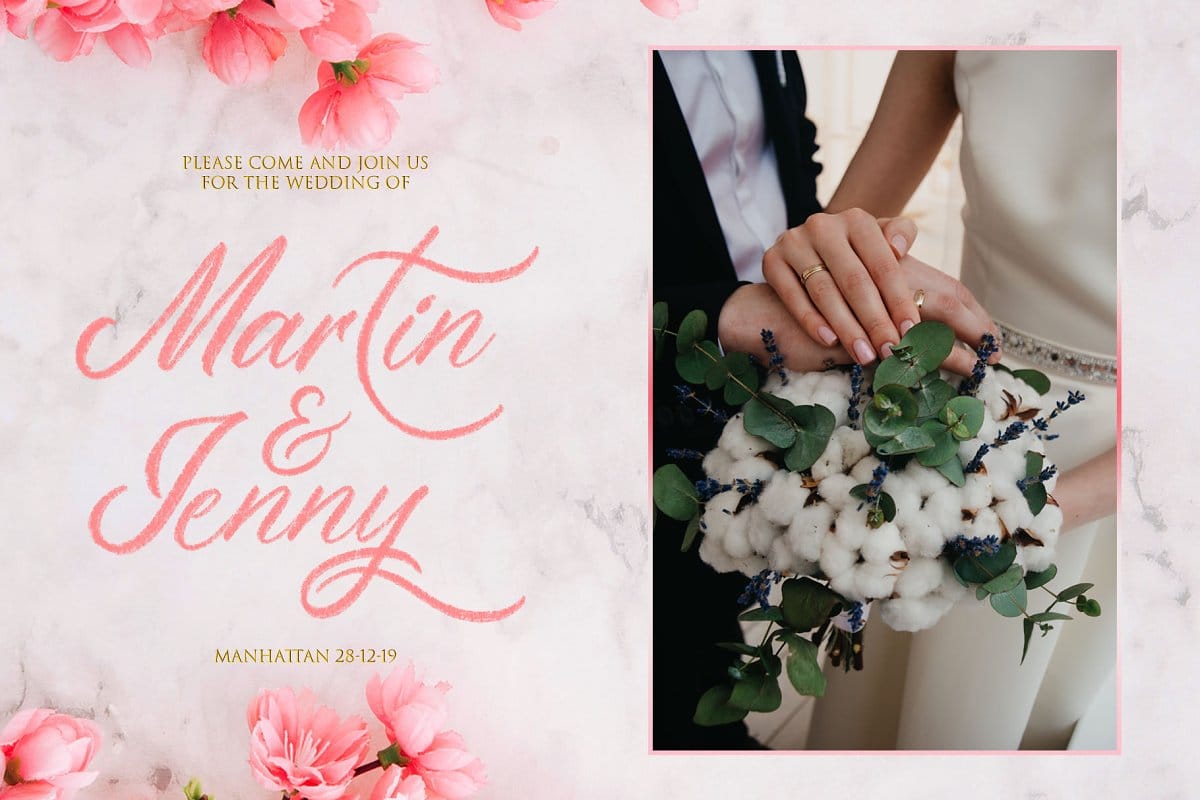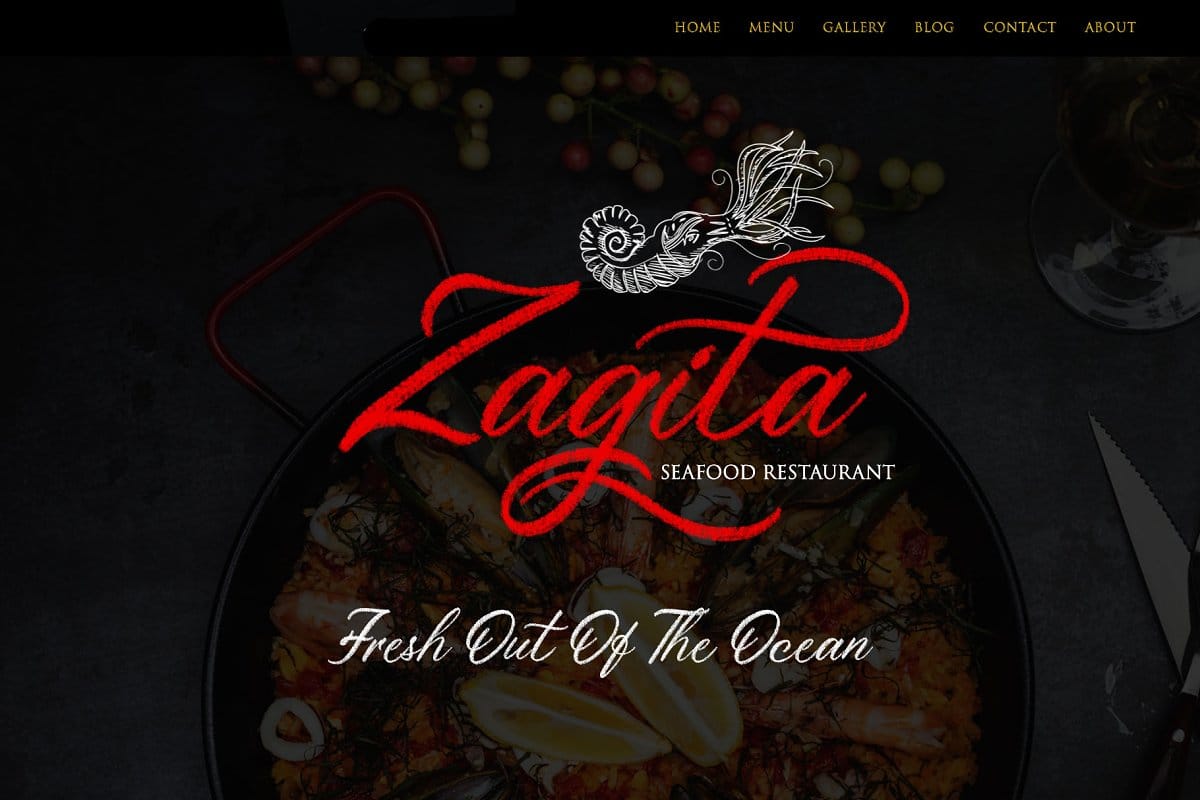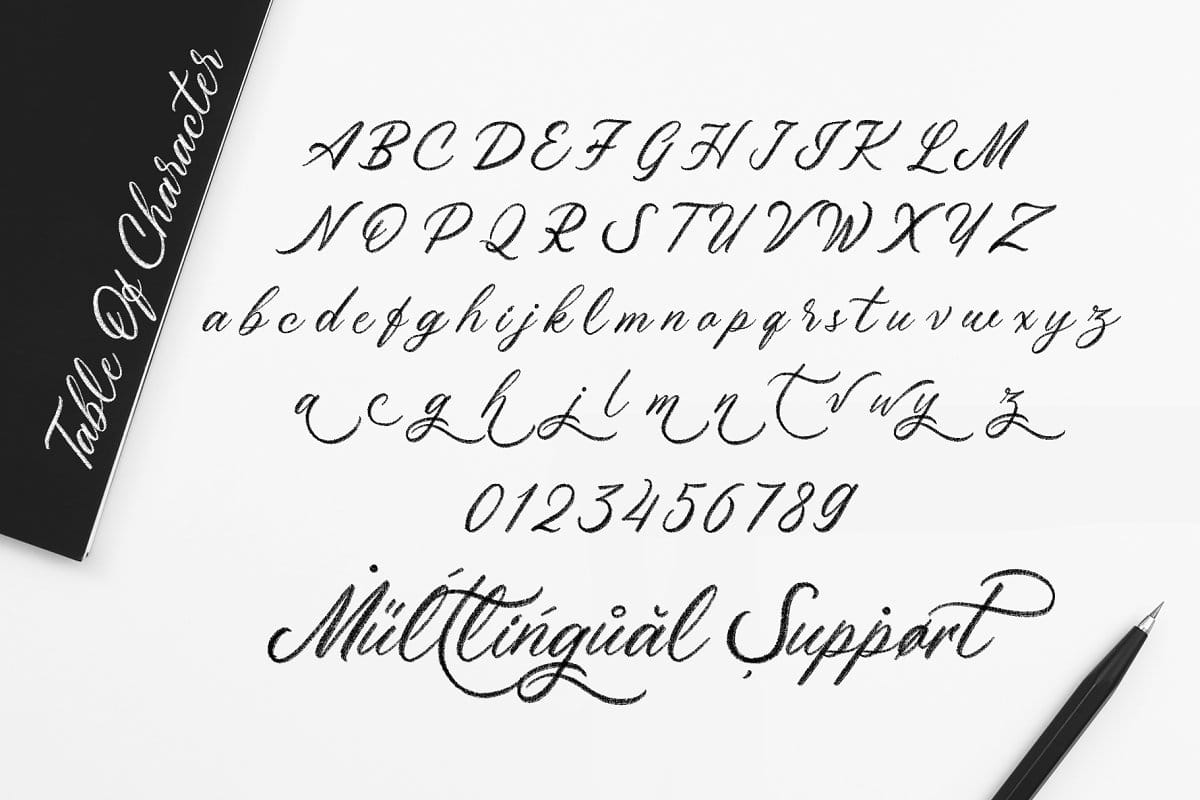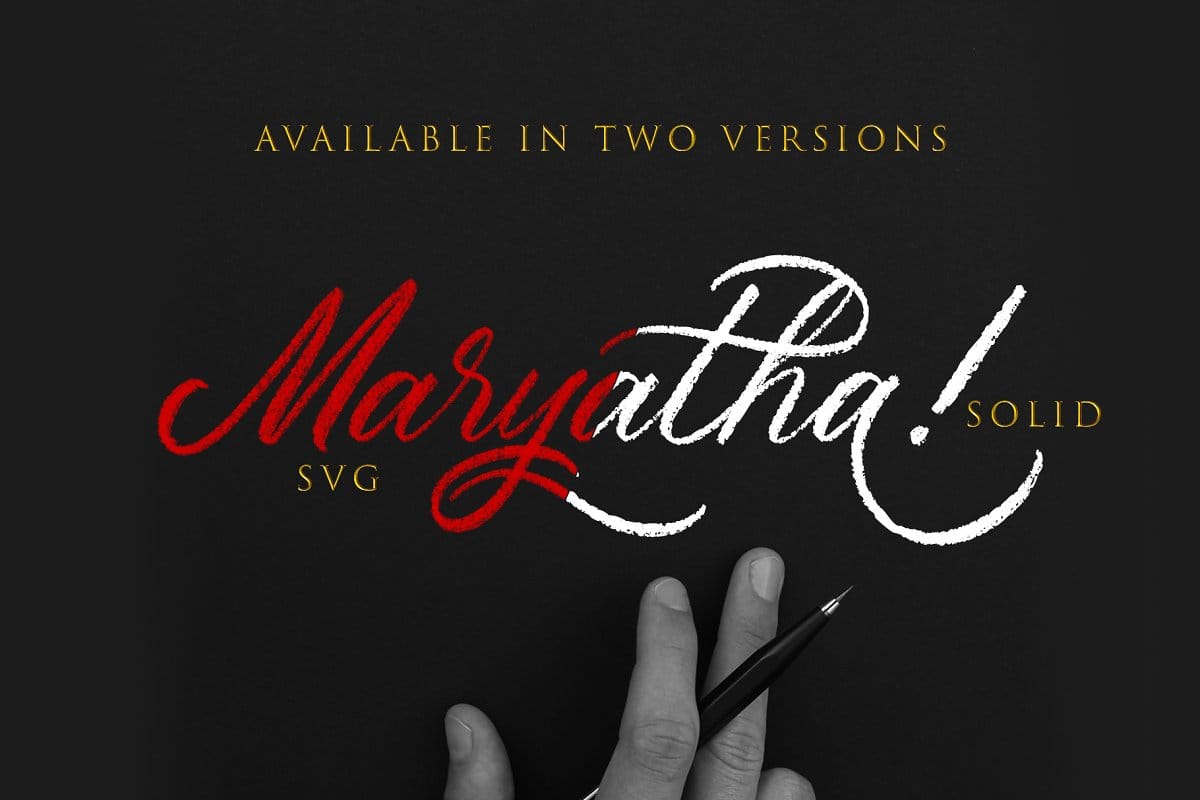
SVG Font Maryatha là một font chữ rất đẹp, với thiết kế dạng kiểu bằng bút chì màu chất lượng cao làm cho phông chữ này trông giống như chữ viết tay của bạn. Bạn có thể sử dụng font chữ này trong các thiết kế Typo, Poster hoặc bất cứ thứ gì bạn muốn tạo ra.